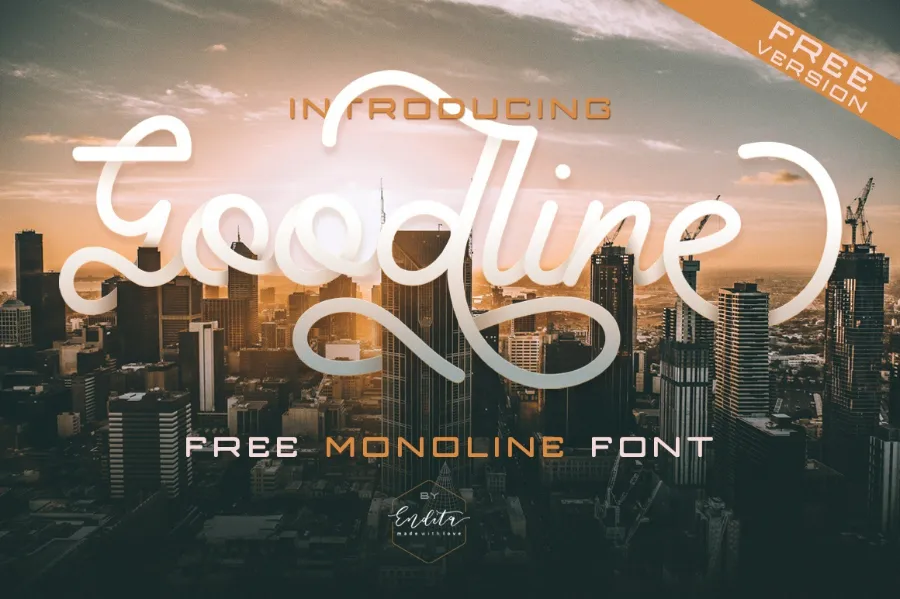
Goodline Font – Download Grátis
Estamos extremamente felizes por você ter demonstrado interesse na Goodline Font. Esta elegante tipografia é perfeita para aqueles que desejam criar mensagens distintas e criativas em produtos variados, seja logotipos, cartazes ou até mesmo selos personalizados. Goodline foi projetada pela Hamilton e partilhada pela Endita, apresentando uma fonte simples com muitas alternativas de caracteres e ligaturas. Com algumas aberturas (swashes) adicionadas, além de ferramentas templates de logo editáveis e vetores, você pode explorar todas as possibilidades criativas. Esta font é extremamente versátil e adequada para usar em diferentes tipos de projetos, como logotipos, cartazes, camisetas, identidade corporativa, cartões de agradecimento ou selos personalizados. Sem dúvida, Goodline Font é uma ótima escolha para quem busca um toque único ao trabalhar com letras e design gráfico em português brasileiro.